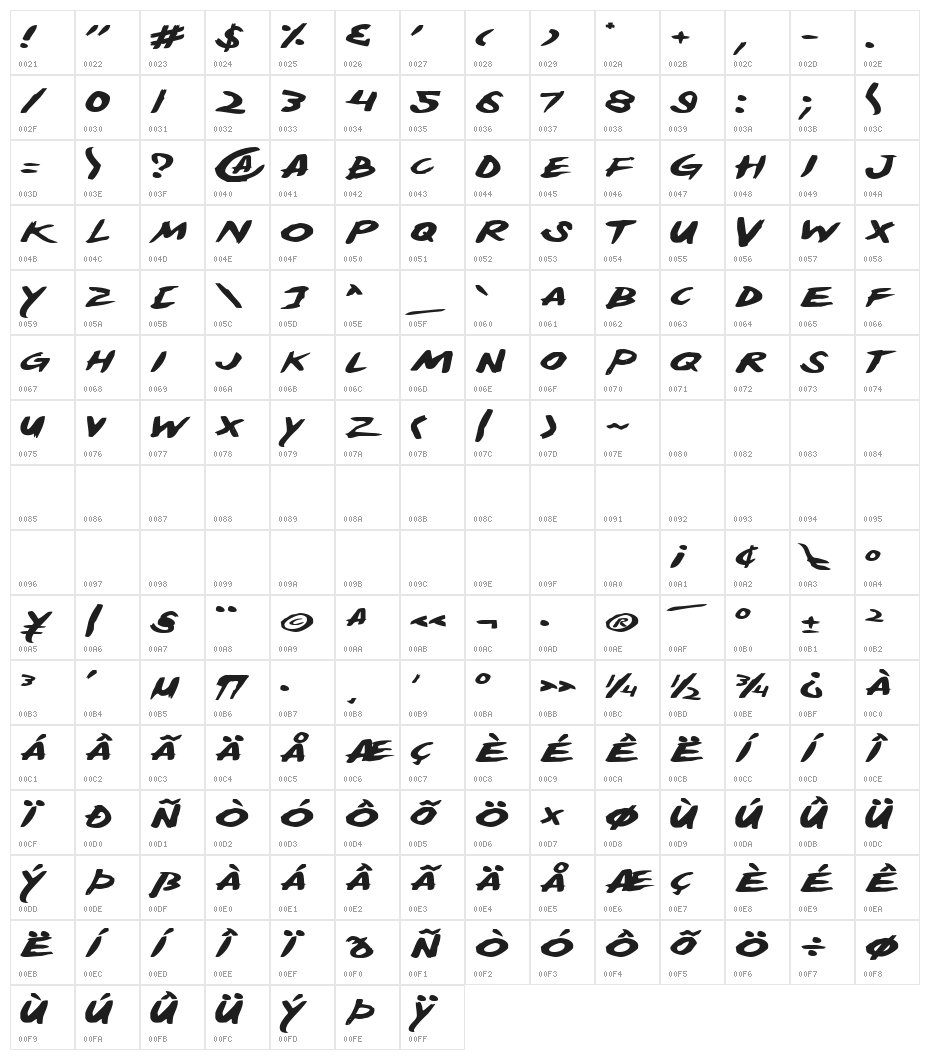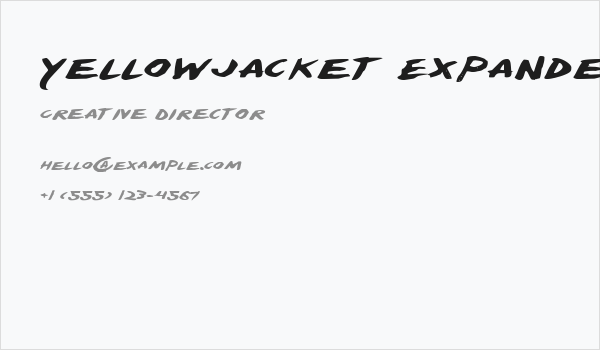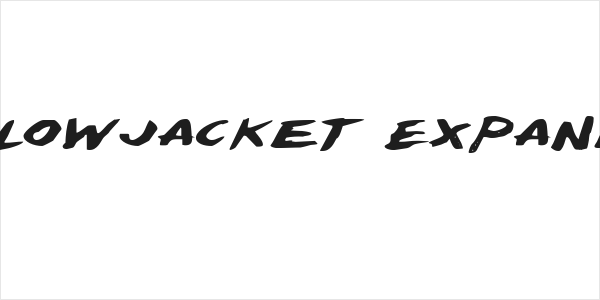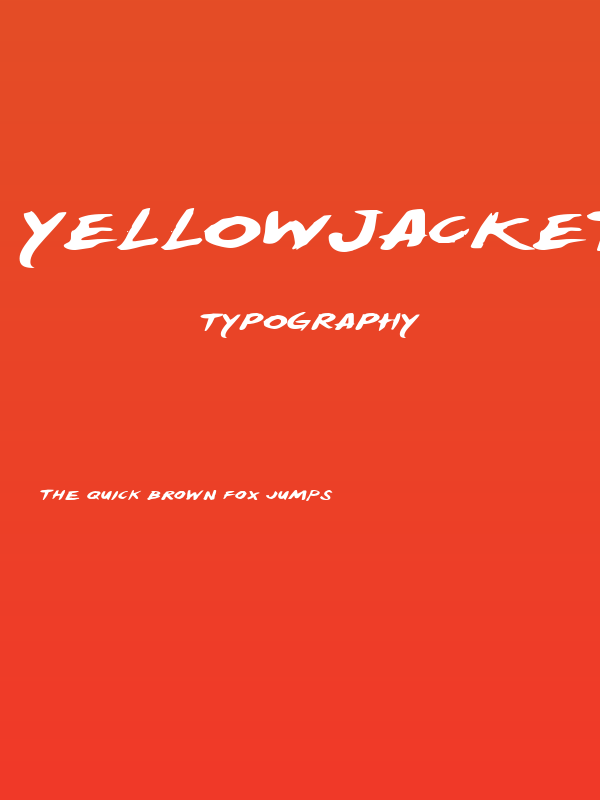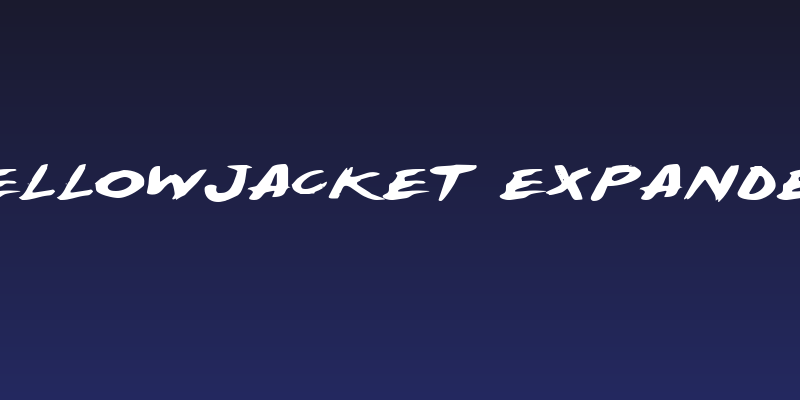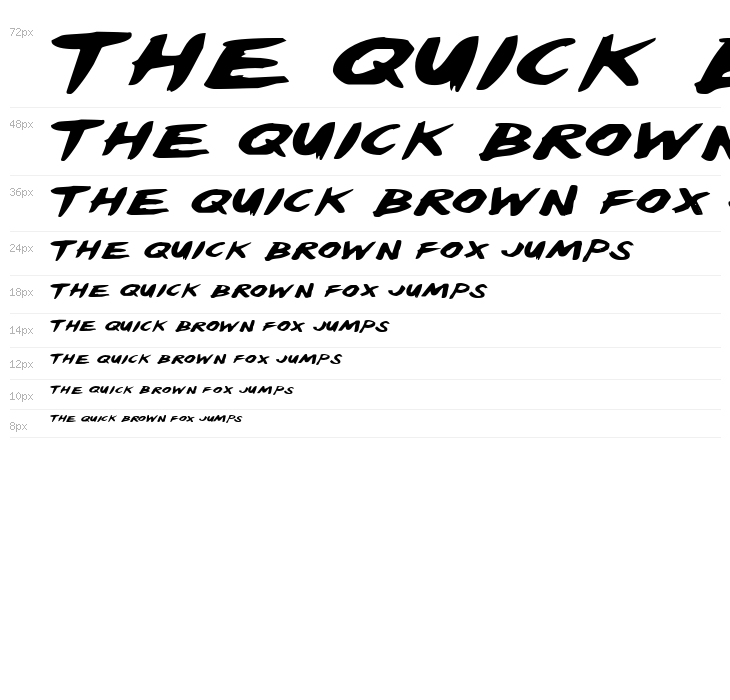
Yellowjacket Expanded Font
| Anwendungsfall | Logos, Headlines, Posters |
| Vorgeschlagene Projekte | Ideal for branding, posters, creative designs, and any project needing a bold artistic touch. |